Font chữ là yếu tố quyết định poster có thu hút hay không. Một poster đẹp không chỉ cần hình ảnh bắt mắt, bố cục rõ ràng mà còn cần font chữ phù hợp với thông điệp, ngành hàng và cảm xúc muốn truyền tải. Dưới đây là danh sách 25+ font chữ cho poster đẹp, dễ dùng, phù hợp cho thiết kế quảng cáo, sự kiện, thời trang, giáo dục, ẩm thực, công nghệ và thương hiệu cao cấp.
Nhóm font hiện đại, dễ đọc cho poster chuyên nghiệp
1. Montserrat
Montserrat là font Sans Serif hiện đại, gọn gàng và dễ đọc. Font này phù hợp với poster doanh nghiệp, khóa học, hội thảo, tuyển dụng, sự kiện công nghệ và các thiết kế cần sự chuyên nghiệp. Ưu điểm lớn của Montserrat là có nhiều độ đậm, dễ tạo phân cấp giữa tiêu đề, phụ đề và nội dung phụ.
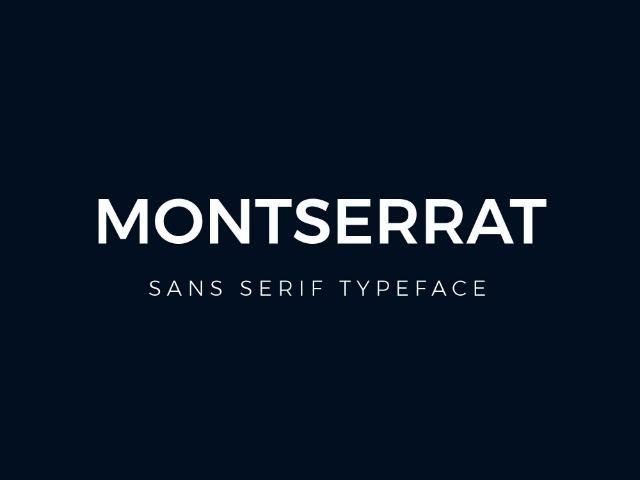
2. Lato
Lato có dáng chữ mềm hơn Montserrat, tạo cảm giác thân thiện nhưng vẫn chuyên nghiệp. Đây là lựa chọn tốt cho poster giáo dục, dịch vụ, chăm sóc sức khỏe, tư vấn, hội thảo hoặc các thương hiệu cần sự gần gũi.
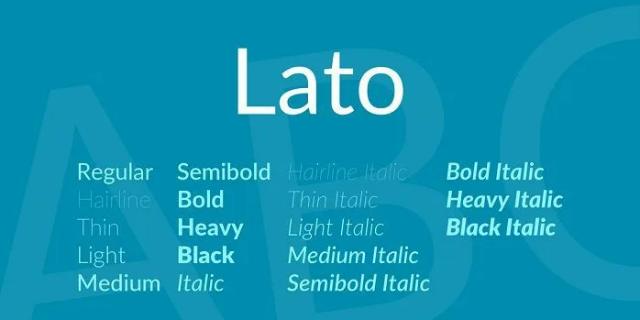
3. Roboto
Roboto là font dễ dùng, dễ đọc và an toàn cho nhiều kiểu thiết kế. Với poster chứa nhiều thông tin, Roboto giúp nội dung rõ ràng, không bị rối mắt. Font này phù hợp với poster công nghệ, app, dịch vụ số, thông báo, chương trình khuyến mãi.
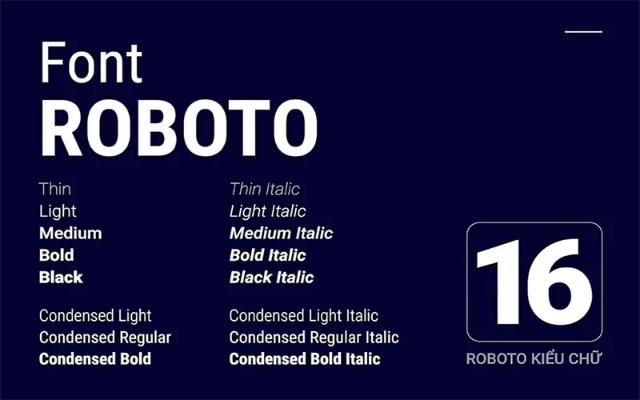
4. Oswald
Oswald có dáng chữ hẹp, cao và mạnh. Font này rất hợp với tiêu đề poster lớn, poster thể thao, sự kiện, sale, khai trương hoặc các thiết kế cần tạo cảm giác chắc, gọn và nổi bật.
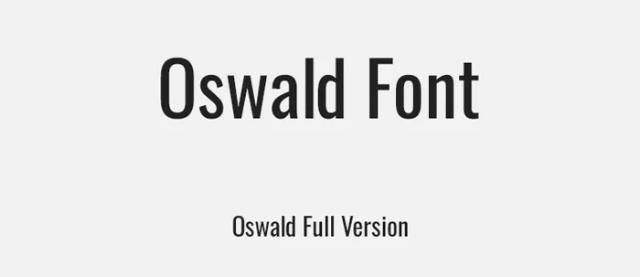
5. Futura
Futura mang phong cách hình học, hiện đại và tinh tế. Font này phù hợp với poster thời trang, kiến trúc, nội thất, công nghệ và các thương hiệu theo đuổi hình ảnh tối giản. Khi dùng Futura, poster thường có cảm giác sạch, sang và có tính thiết kế cao.
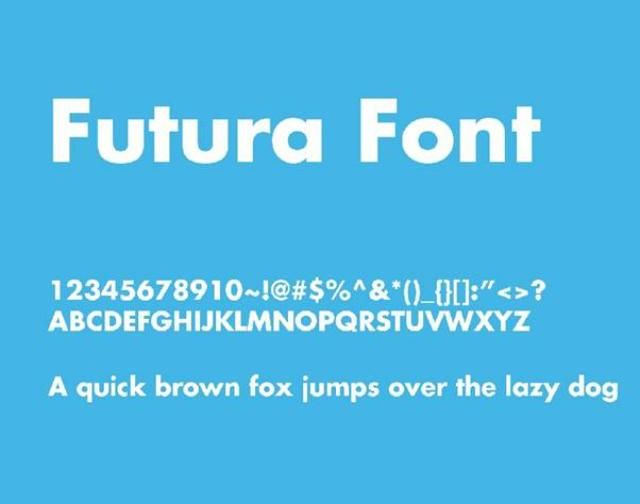
6. Helvetica Neue
Helvetica Neue là lựa chọn kinh điển cho các thiết kế cần sự cân bằng, rõ ràng và chuyên nghiệp. Font này phù hợp với poster thương mại, thương hiệu, sự kiện doanh nghiệp, triển lãm hoặc các ấn phẩm có bố cục tối giản.
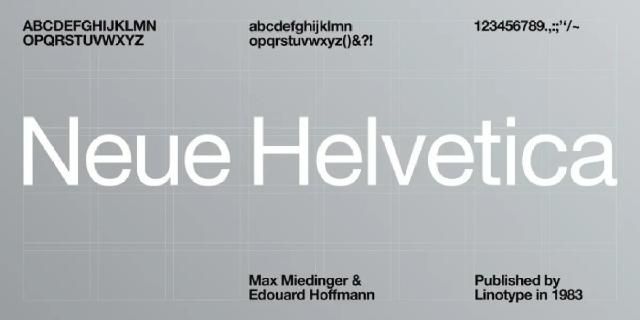
7. Proxima Nova
Proxima Nova kết hợp giữa phong cách hình học và cảm giác thân thiện. Font này hợp với poster công nghệ, marketing, giáo dục, startup và các thiết kế hiện đại. Nếu muốn poster nhìn sạch nhưng không quá khô, Proxima Nova là lựa chọn đáng dùng.
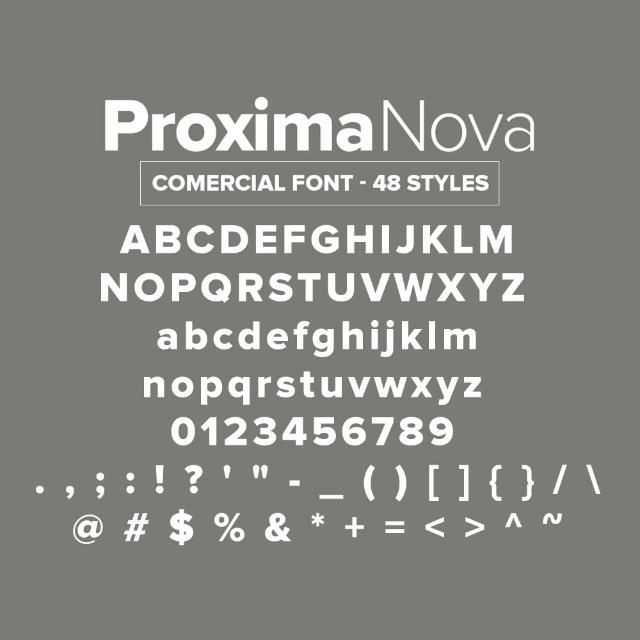
Nhóm font tiêu đề mạnh, gây chú ý nhanh
8. Bebas Neue
Bebas Neue là font in hoa nổi bật, rất hợp cho tiêu đề poster. Font này thường được dùng trong poster quảng cáo, sự kiện, thể thao, âm nhạc, phim ảnh hoặc chương trình giảm giá. Ưu điểm là mạnh, gọn và bắt mắt ngay từ cái nhìn đầu tiên.
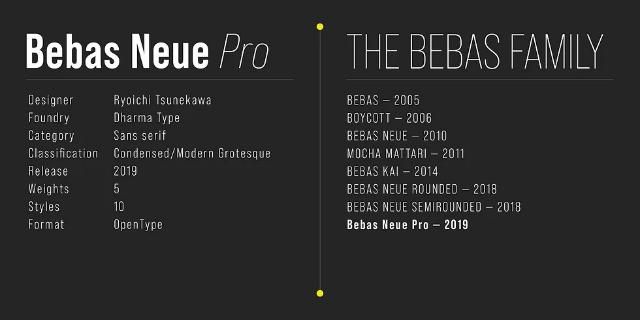
9. Impact
Impact có nét chữ dày, nén và rất mạnh. Font này phù hợp với slogan ngắn, thông điệp khẩn cấp, poster thể thao, chiến dịch quảng cáo hoặc các thiết kế cần gây chú ý cực nhanh. Không nên dùng Impact cho đoạn văn dài vì dễ gây nặng mắt.
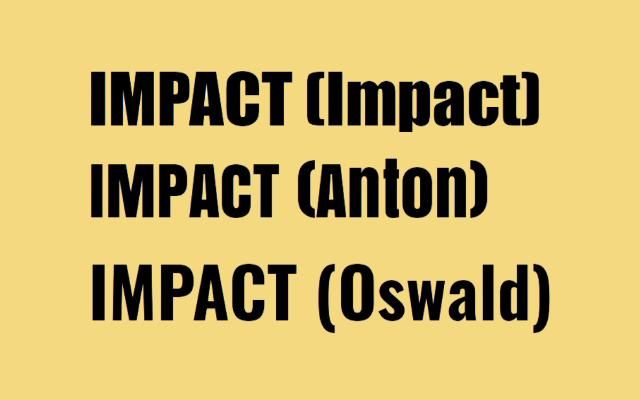
10. Gotham
Gotham mang cảm giác hiện đại, chắc chắn và cao cấp. Font này phù hợp với poster thương hiệu, sự kiện doanh nghiệp, bất động sản, công nghệ và truyền thông chính trị. Gotham giúp thiết kế trông có hệ thống và đáng tin cậy hơn.
11. TH Chrone
TH Chrone là font đậm, sắc nét, hợp với tiêu đề chính của poster. Font này nên dùng cho các thiết kế cần sự mạnh mẽ như poster sự kiện, quảng cáo sản phẩm, thể thao, game hoặc chiến dịch bán hàng.
12. TH Castio
TH Castio có cá tính rõ, phù hợp với poster cần tạo ấn tượng mạnh. Font này hợp với lĩnh vực thời trang, âm nhạc, lifestyle, sự kiện trẻ hoặc các thương hiệu muốn tạo cảm giác khác biệt.
13. TH Kairo
TH Kairo có nét chữ dày, khỏe và năng động. Font này phù hợp với poster thể thao, phòng gym, giải đấu, sự kiện ngoài trời hoặc các chương trình cần truyền tải tinh thần quyết liệt.
Nhóm font sang trọng, cổ điển cho poster cao cấp
14. Playfair Display
Playfair Display là font Serif thanh lịch, có nét đậm mảnh rõ ràng. Font này phù hợp với poster thời trang, mỹ phẩm, nghệ thuật, triển lãm, nhà hàng cao cấp hoặc sự kiện sang trọng. Khi kết hợp với font Sans Serif đơn giản, Playfair Display tạo hiệu ứng rất đẹp.
15. Bodoni
Bodoni mang vẻ cổ điển, sắc sảo và sang trọng. Font này hợp với poster thời trang, nước hoa, spa, thẩm mỹ viện, trang sức và các thương hiệu cao cấp. Bodoni nên dùng cho tiêu đề hoặc điểm nhấn, không nên dùng quá nhiều ở phần nội dung.
16. Abril Fatface
Abril Fatface là font Display có nét dày ấn tượng, tạo cảm giác cổ điển nhưng vẫn hiện đại. Font này phù hợp với poster thời trang, nghệ thuật, tạp chí, sự kiện đặc biệt hoặc các thiết kế cần tiêu đề thật nổi bật.
17. Trajan Pro
Trajan Pro mang cảm giác trang trọng, cổ điển và có tính biểu tượng. Font này phù hợp với poster phim, sự kiện văn hóa, lịch sử, triển lãm, lễ trao giải hoặc các thiết kế cần vẻ uy nghiêm.
18. DVN Silk Việt hóa
DVN Silk Việt hóa là font Serif tinh tế, mềm mại và sang. Font này phù hợp với poster thời trang, mỹ phẩm, spa, thiệp mời, tạp chí hoặc nhận diện thương hiệu cao cấp. Ưu điểm là có bản Việt hóa nên hiển thị tiếng Việt tốt hơn trong thiết kế.
Danh sách trên gồm hơn 20 font chữ cho poster đẹp, phù hợp nhiều phong cách thiết kế khác nhau. Nếu cần sự hiện đại và an toàn, hãy chọn Montserrat, Roboto, Lato hoặc Proxima Nova. Nếu cần poster nổi bật mạnh, hãy dùng Bebas Neue, Impact, Oswald hoặc TH Chrone. Nếu muốn tạo cảm giác cao cấp, Playfair Display, Bodoni, DVN Silk và DVN Astera là lựa chọn đáng ưu tiên. Quan trọng nhất, font chữ phải phù hợp với thông điệp, ngành hàng và đối tượng người xem của poster.